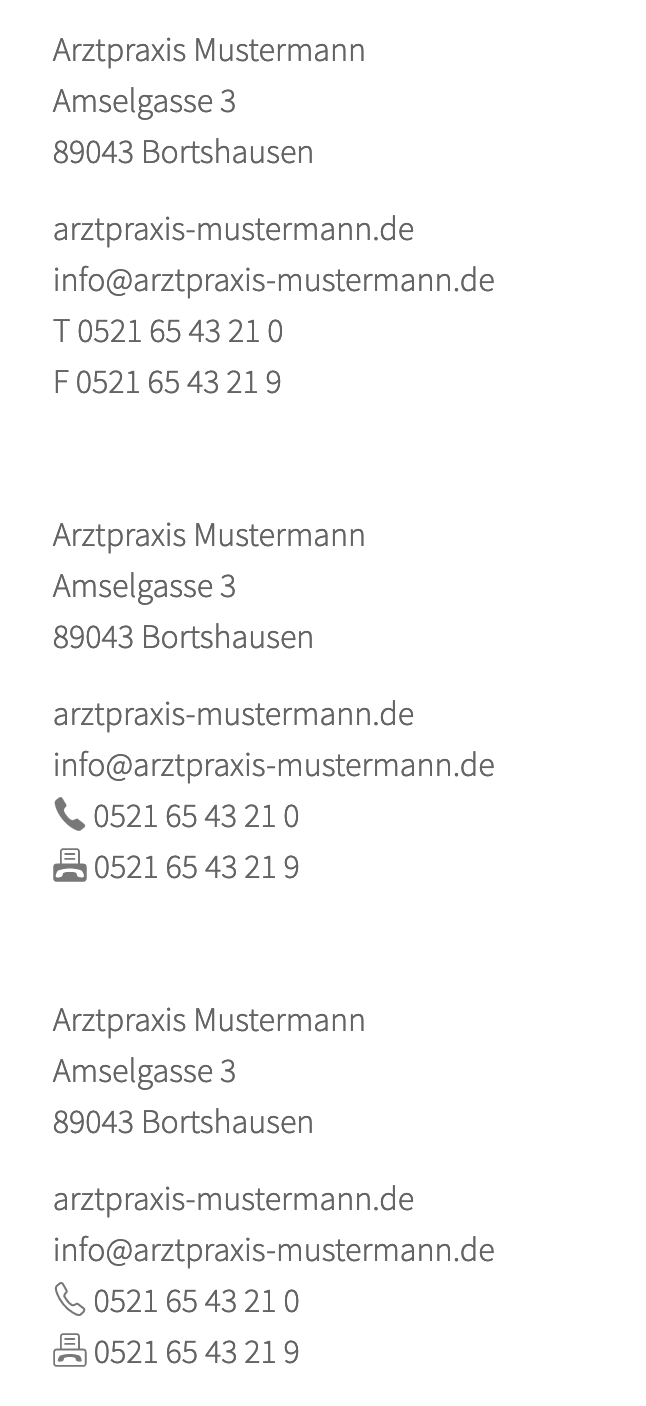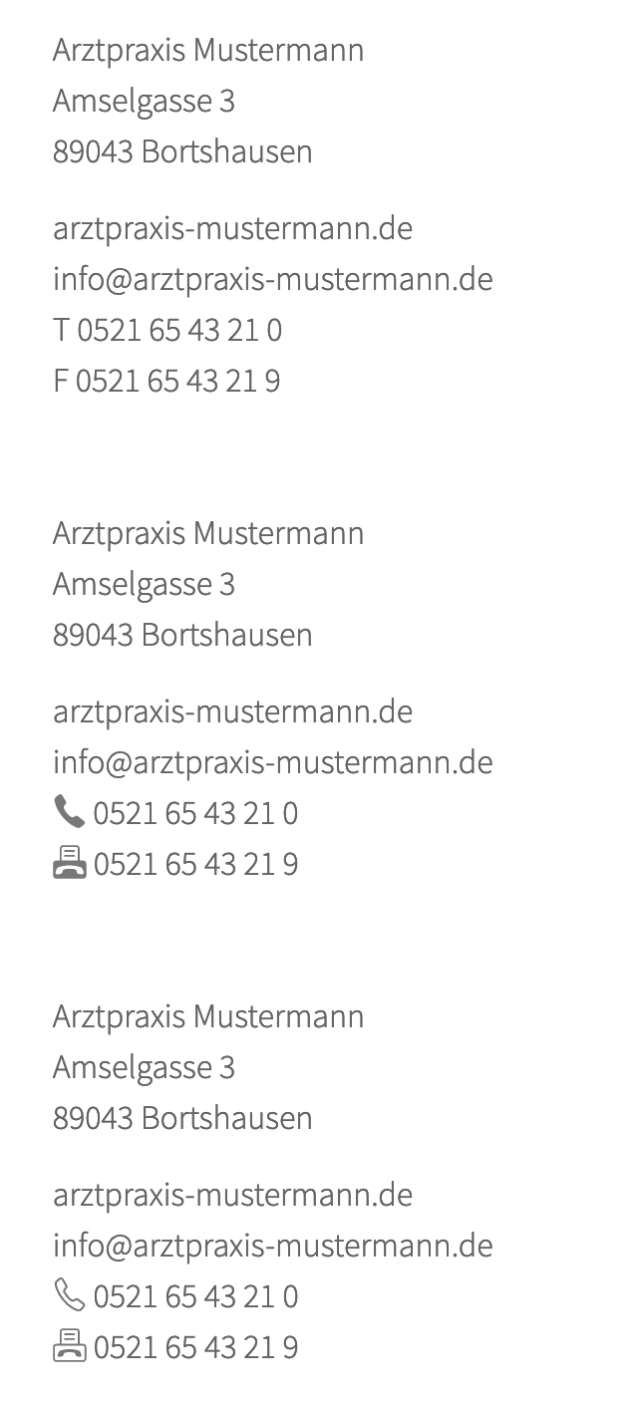
Kennzeichnung einer Faxnummer per Symbol?
Ich würde doch noch mal eine Lanze für die Verwendung von Symbolen brechen wollen. In der Regel benutze ich bei Faxnummern das Symbol für Drucken* – und die meisten Symbolschriften** haben unterschiedliche und gut unterscheidbare Symbole für (Festnetz-)Telefon und Mobiltelefon.
** z.B. Ligature Symbols, Iconic Font (iconmonstr), Material Icons …
Ja klar. Das Drucker-Symbol konzentriert sich auf die eine Funktion, durch die sich ein Fax vom (Sprach-)Telefon unterscheidet. Das ist natürlich dem »Bürotelefon mit äußerst subtil angedeuteter Papierknickecke« überlegen.
Überhaupt gefällt mir dein Beispiel gut. Jede Person hat eine Telefonnummer. Für die, die es genauer wissen wollen, gibt es den subtilen Hinweis durch das Symbol, dass eine Person über ein Mobiltelefon kommuniziert. Aber es gibt eben kein Dilemma, wenn ich einfach nur wissen, will, wie ich Person X jetzt anrufen kann. Da ist die Art des Telefons ja egal.
Ich finde das im Ausgangsposting vorgestellte Symbol für FAX besser, weil es den Telefonhörer enthält und sich so besser vom Drucker-Symbol abgrenzt.
Die Bedeutung ist damit näher an der Funktionsweise des Gerätes. Telefonnummer mit Sonderfunktion - mit Textübertragung.
Aber das sind natürlich Feinheiten. Wie andere hier im Thread sehe ich auch, dass auch ein Druckersymbol im Kontext wohl von den meisten Nutzern auf Anhieb richtig interpretiert würde.
Zu Deiner Beispielseite:
Für Menschen mit Sehbehinderungen, die bei Bildern mit Bedeutung darauf angewiesen sind, dass diese transportiert wird, wäre die Information Fax/Telefon unzugänglich.
Denn das Symbol wird via "generated content" eingefügt. Einen "Alternativtext" gibt es nicht.
Kommt drauf an, würde ich sagen. Handelt es sich um die Nummer eines Anschlusses, an dem ein Kombigerät hängt, an das man also sowohl Faxe schicken als auch Telefonanrufe absetzen kann, ist ein Symbol mit 📞 genau richtig. Ist es aber nur ein Faxgerät, an dem bei einem Sprachanruf nie jemand rangehen wird, was soll dann der Telefonhörer symbolisieren? Dann ist das Gerät doch in der Tat nichts als ein Drucker (der seine Daten über eine Telefonleitung statt USB oder ein altes Druckerkabel bekommt).
Ich bin sicher, dass das Druckersymbol mit Hörer eher mit einem Faxgerät assoziiert wird als ein Druckersymbol ohne Hörer.
Die Verständlichkeit von Symbolen hängt ja nicht in erster Linie allein von ihrer sachlichen Korrektheit ab, sondern von den Konzepten und Sehgewohnheiten der Betrachter.
Wenn es denn als solches erkannt wird. Ich sehe in dem Font-Awesome-Symbol ohne Kontext weder Hörer noch Drucker.
Über das Fax-Symbol aus dem Font Awesome sprach ich auch nicht. Das sehe ich genauso wie Du. Ich hätte auch Mühe es als Fax zu identifizieren.
Ich sprach über das Fax-Symbol aus dem ersten Posting.
Axso. :aschehaupt:  Ja, das ist auch OK, obwohl ich da auch eher einen Drucker mit leicht übertriebenem Griff fürs Papierfach sehe. :-?
Die Geschäftsführerin kann ich auf dem iPad anrufen 🤔Das Symbol finde ich wenig passend und, dass es eine Mobilnummer ist, erkennt man doch ...
Wie gesagt aus Gestaltersicht finde ich Icons selten gut, die wirken für mich immer sehr Technokratisch und erinnern mich an die ersten ungestalteten Ingenieur-Webseiten oder Briefpapier aus dem Copyshop.
Voilá, zwei Sets.
Eine befreundete Grafikerin, Stefanie Weyer, war so nett und hat auf meinen Wunsch, angelehnt an das UTF-8-Fax-Symbol, zwei Fax-Symbole als SVG erzeugt. Einmal als Umriss und einmal mit "gefülltem Faxgerätgehäuse". Der Hörer aus dem Fax dient dann für das Set als Telefon-Symbol. Ebenfalls einmal als Umriss, einmal "gefüllt".
Schriftfont: Source Sans Pro
Kritik ist wie immer willkommen.
Das ist handwerklich sicher ordentlich gemacht und deshalb auch keine Kritik an der Grafikerin. Mich überzeugt nur die generelle Gestaltung des Symbols nicht. Ich habe noch nie ein Faxgerät gesehen, bei dem der Hörer vorne so quer liegt. Und daher erkenne ich da auch keinen Telefon-/Fax-Hörer und in dem Gesamtsymbol dann auch kein Faxgerät. Es sieht halt einfach wie ein Drucker aus. Im Kontext wird das freilich meist ausreichen.
Ich belegte übrigens nur die Telefonnummern mit »Klickmöglichkeit«. Bei FAX gibt es so unterschiedliche Versandmöglichkeiten, dass sich nur selten das richtige Programm öffnete.